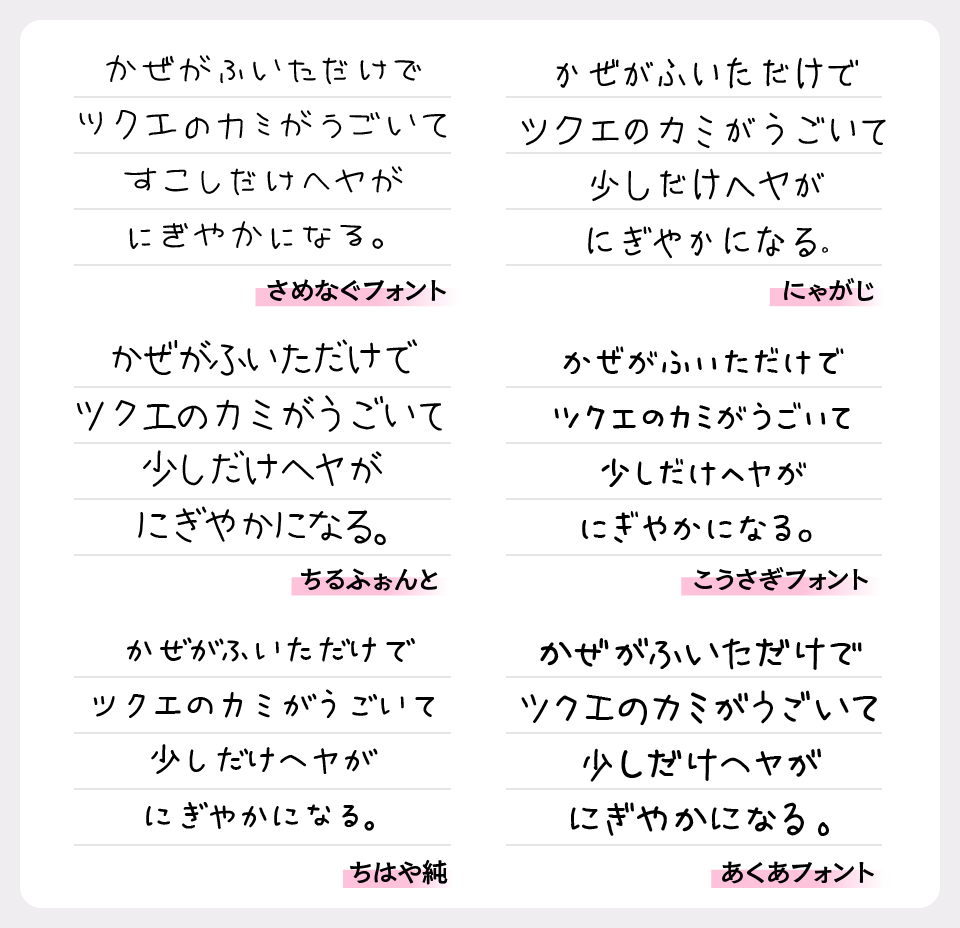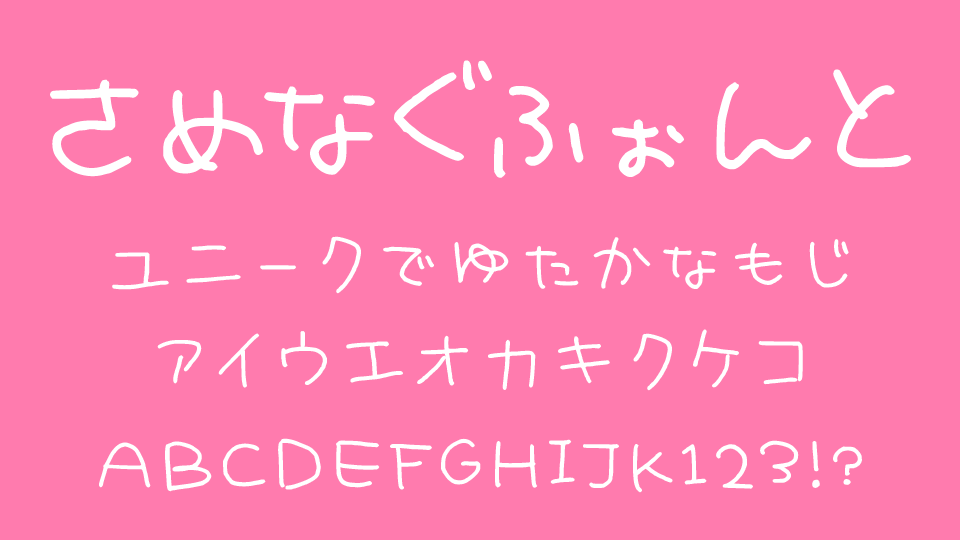
さめなぐふぉんとフォントは、作者楪のどかさんによる、丸みがあり細く軽やかな線で描かれた、自然体の可愛らしい手書きフォントです。
文字にはわずかな揺らぎや不揃いさがあり、ノートやメモへさらりと書いたような親しみやすい雰囲気を演出しています。飾り気のないシンプルなデザインだからこそ、言葉そのものの温度や優しさを素直に伝えてくれるフォントです。
手紙やメッセージカード、ブログ、エッセイ、イラスト作品、SNS投稿など、日常に寄り添うデザインにぴったりなフォントです。
さめなぐるおしごとフォントを、ほかの自然体の手書きフォントと比較してみると、飾りすぎない素朴さと、やさしい書き文字の雰囲気が特徴のフォントとなっています。
比較フォントは、「にゃがじ」「ちるふぉんと」「こうさぎフォント」「ちはや純」「あくあフォント」と使用していますが、どれもナチュラルな手書きフォントなので、ぜひあわせてチェックしてみてください。
収録文字は、ひらがな・カタカナ・アルファベット・数字・記号が収録されています。